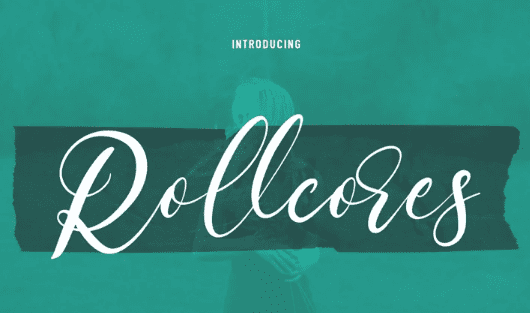
[Fontbundles] Rollcores Script Font (2022)
Rollcores - это современный красивый шрифт для подписи. С высококонтрастным начертанием, веселым характером с небольшим количеством лигатур и стилистических чередований. Чтобы дать вам дополнительную творческую работу. Шрифт Rollcores поддерживает более 100+ языков. Этот шрифт хорош для дизайна логотипов, социальных сетей, названий фильмов, книг, короткого текста, даже длинных букв, и хорош для вторичного текста шрифтом sans или serif. Сделайте потрясающую работу со шрифтом Rollcores.